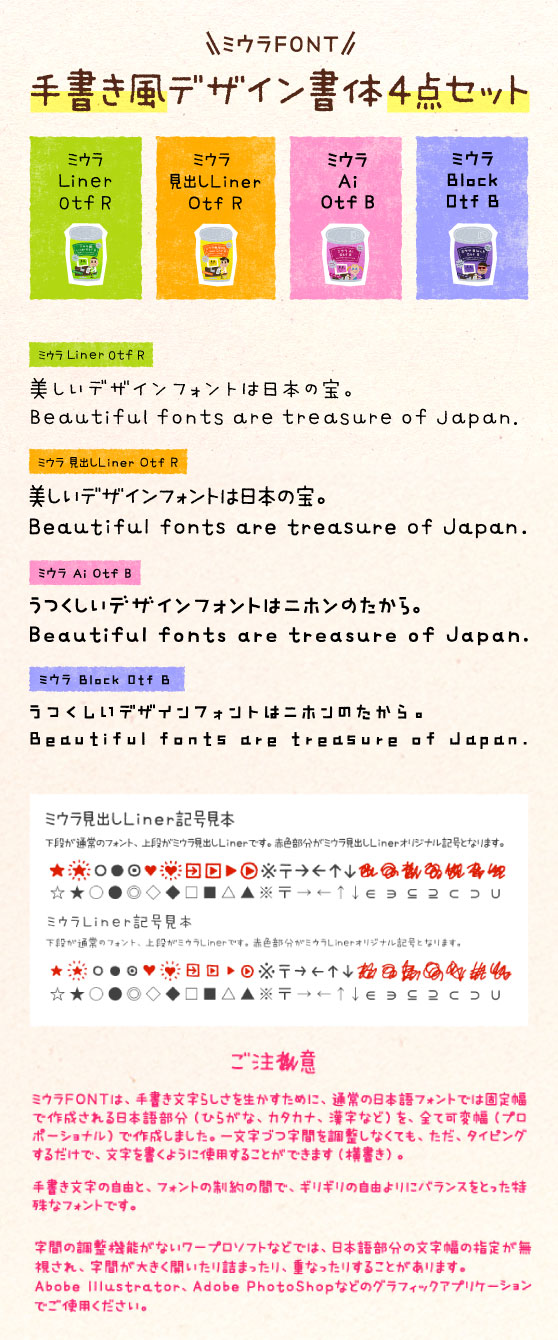
手書き風書体
ミウラFONTの手書き風デザイン書体4点セット
MiuraLinerOtf-R,MiuraMidashiLinerOtf-R,MiuraAiOtf-B,MiuraBlockOtf-B
ミウラLinerOtf R
ひらがなカタカナ、アルファベット、一部の記号、JIS第一水準(2965字)+第二水準以降より219字
ミウラ見出しLinerOtf R
ひらがなカタカナ、アルファベット、一部の記号、JIS第一水準(2965字)+第二水準以降より219字
ミウラAiOtf B
ひらがな・カタカナ・アルファベット・一部のJIS記号
ミウラBlockOtf B
ひらがな・カタカナ・アルファベット・一部のJIS記号
ミウラフォント/モップスタジオの紹介
MopStudioの「ミウラFONT」シリーズは、可変幅と特殊文字が特徴の手書き風デザイン書体です。手書き文字らしさを最大限に表現するため、日本語書体としては異例にも全ての文字を可変幅 (プロポーショナル) で作成した特殊なフォント。「グシャっ」とした書き直し筆跡など、オリジナルの記号も魅力です。